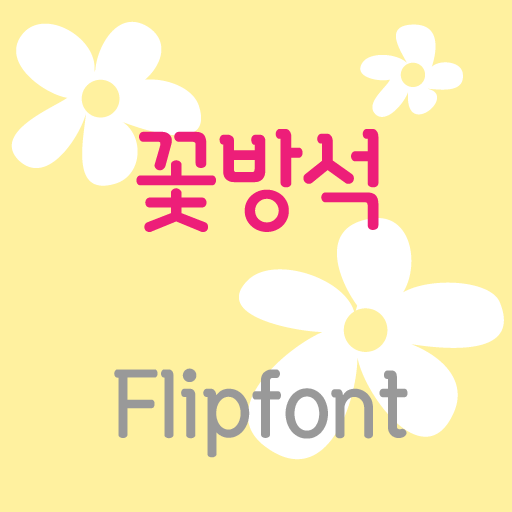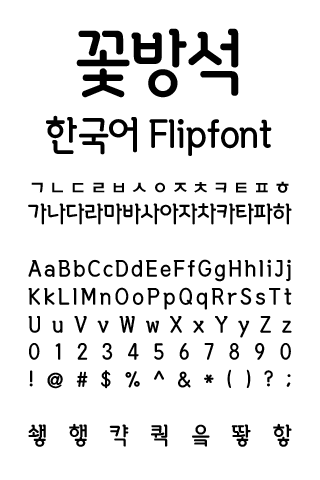
Monotype Imaging Inc. 에서 제공하는 폰트 변경 기능인Flipfont의 폰트 추가 설치 파일입니다. 폰트를 설치하시면 설정 메뉴의 폰트 목록에 해당 폰트가 추가 등록됩니다. Log꽃방석™ 한국어 Flipfont 서체는 부드러운 곡선의 바른모양 서체입니다.